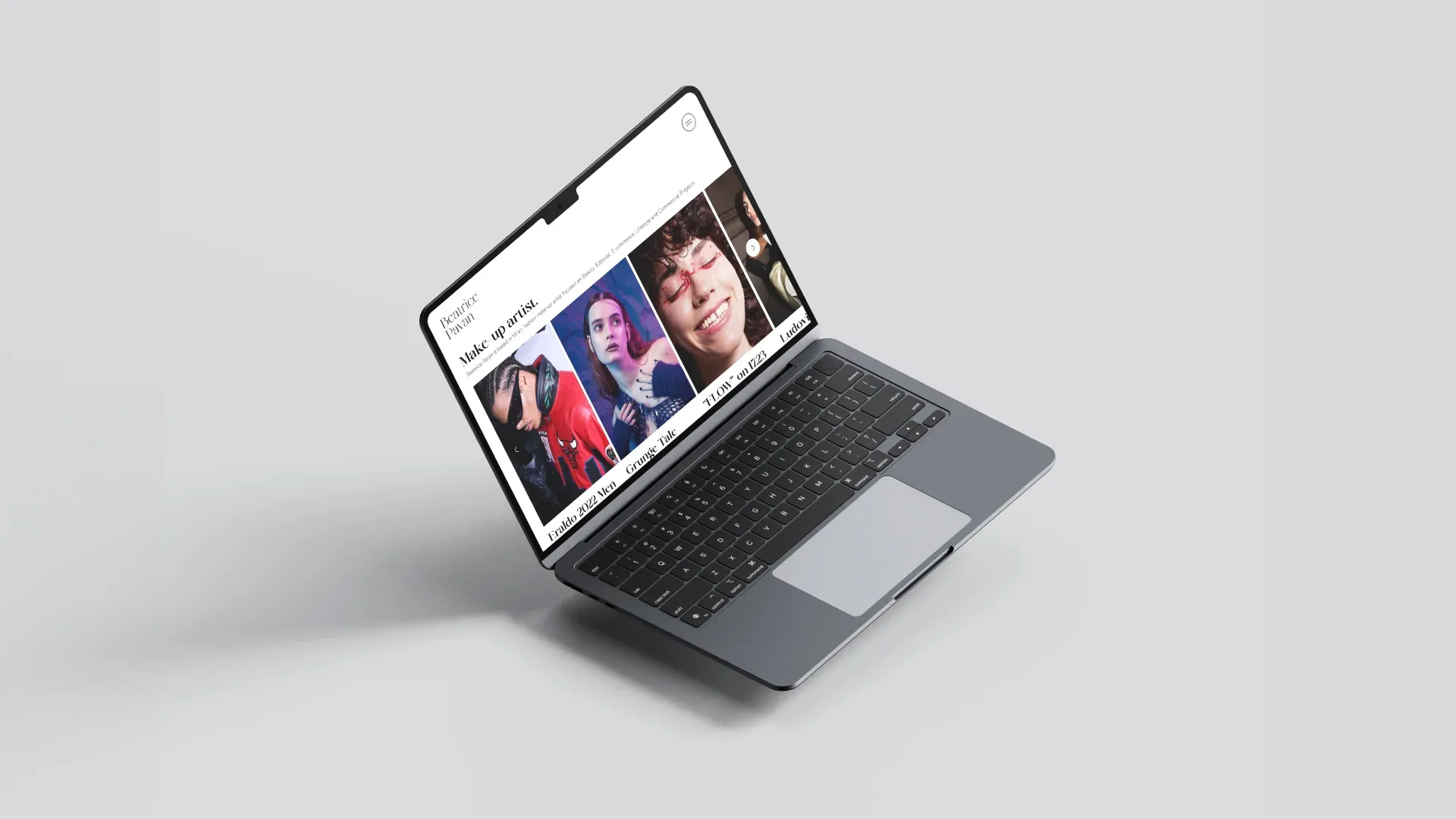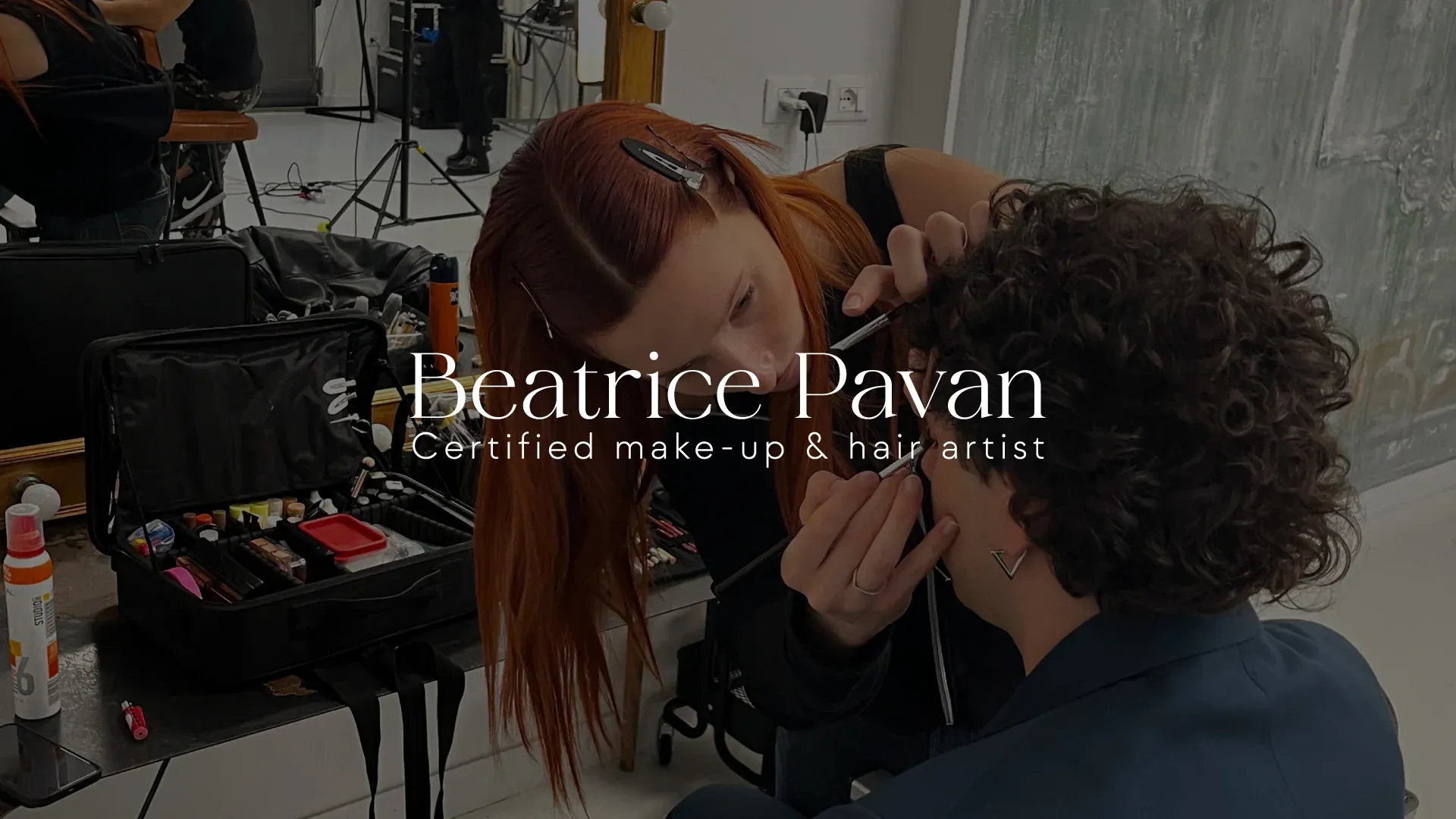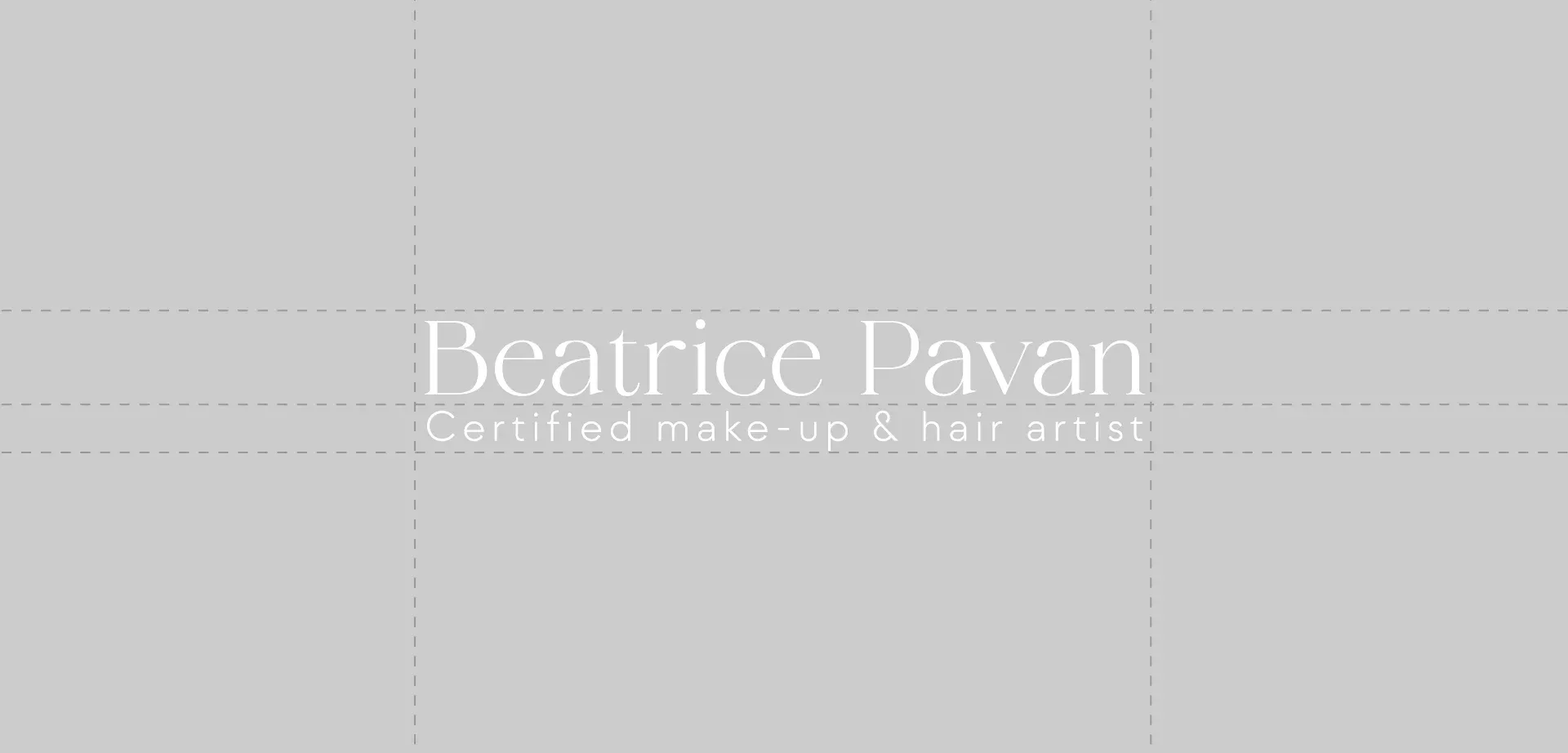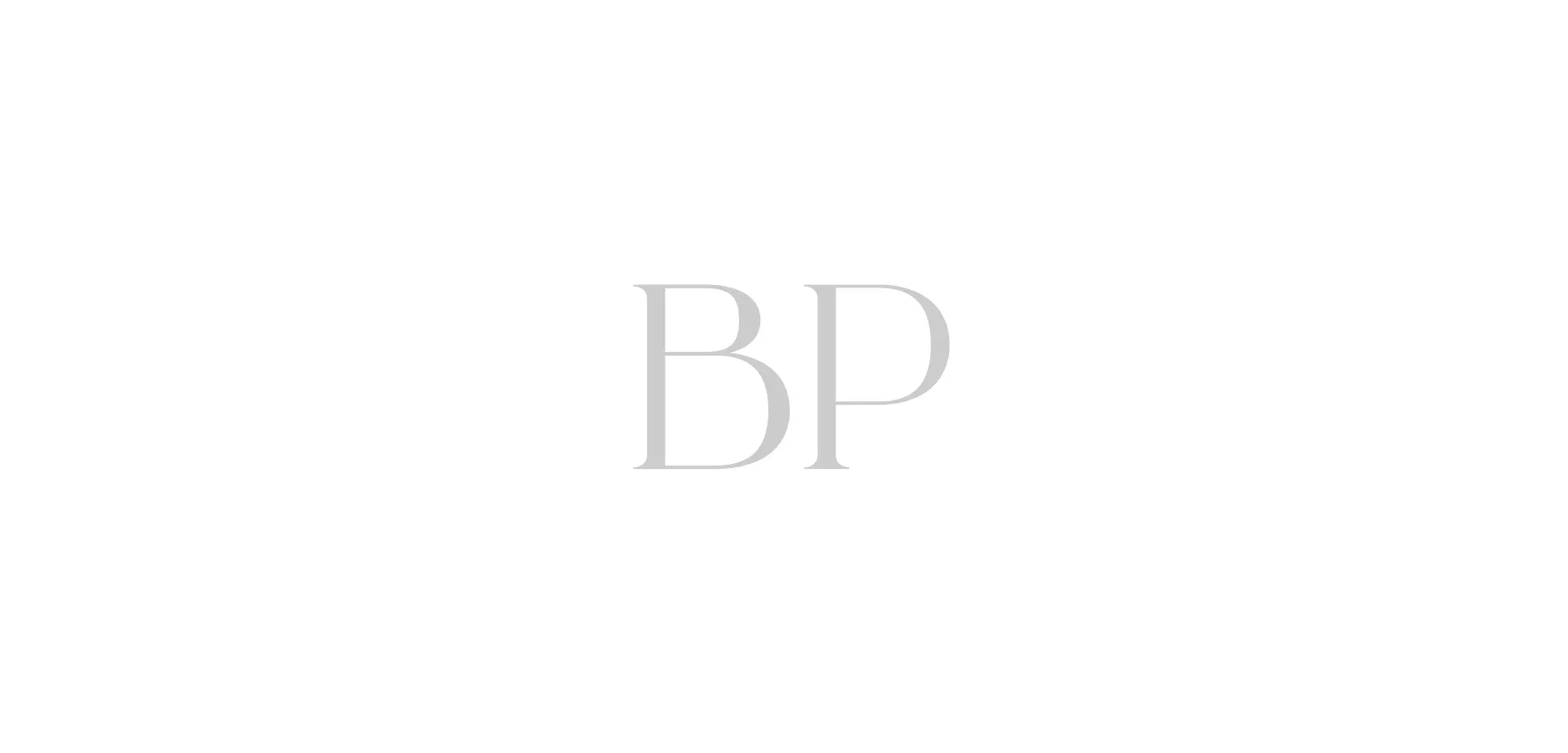
Portfolio web per Beatrice Pavan
Beatrice Pavan è una talentuosa Make-up & Hair Artist di Milano, specializzata in scatti editoriali, e-commerce, lifestyle e fashion. Abbiamo avuto il piacere di collaborare con lei per dare una nuova identità alla sua attività, partendo dalla creazione del logo fino alla realizzazione di un sito web vetrina, che funge anche da portfolio digitale dei suoi progetti più importanti.
Il font, la base dell'idnetità digitale
Abbiamo selezionato con cura un font che potesse trasmettere le emozioni e l'eleganza tipiche del mondo della moda e del beauty. Il risultato è un sito web che non solo funge da vetrina per il lavoro di Beatrice, ma che comunica anche in modo efficace la sua professionalità e creatività.
Far Parlare gli Scatti
Il sito web è stato progettato seguendo una linea guida principale: dare il massimo risalto ai make-up di Beatrice. Per raggiungere questo obiettivo, abbiamo utilizzato un design minimalista e una palette di colori dominata dal bianco. Questo approccio permette di far emergere le immagini in modo preciso e trasparente, mettendo in luce il talento di Beatrice nei vari progetti svolti.